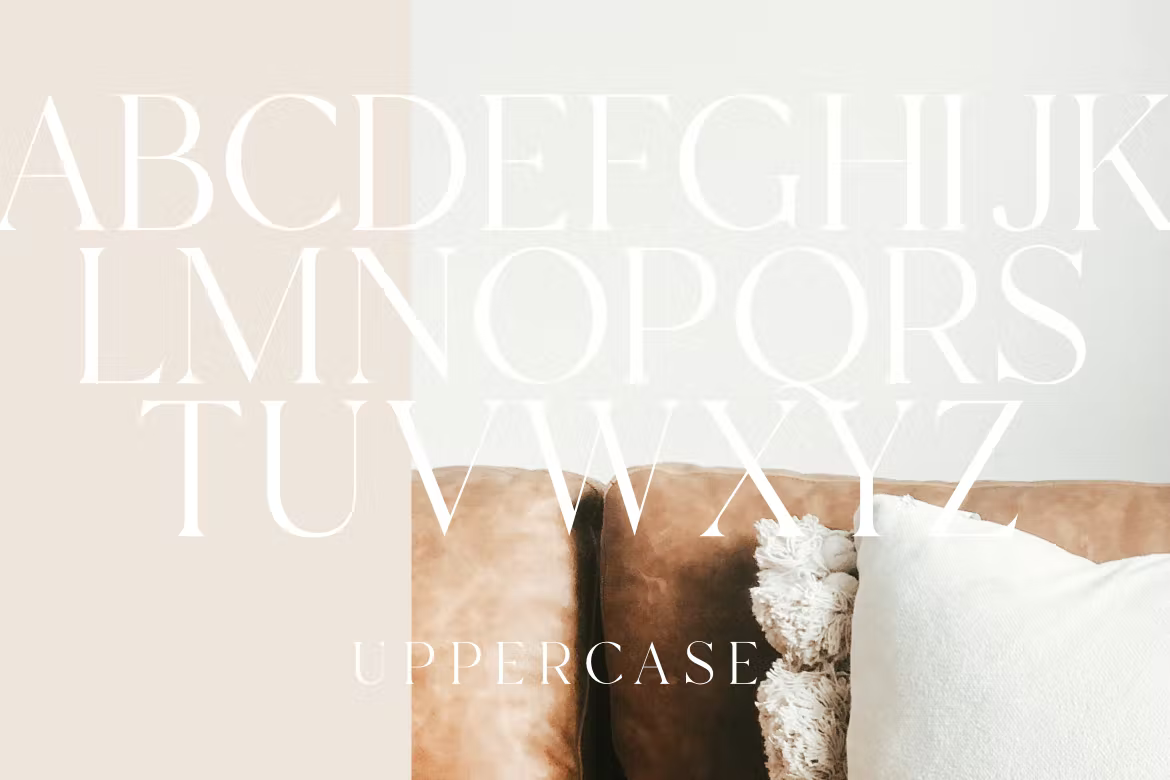
Branch Font
Description de Branch Font
Branch Font Elegant Ligature Font par Sans and Sons présentant notre nouvelle ligature moderne « Branch » avec un style élégant, parfaite pour l’image de marque, les logos, les invitations, les titres de mât et plus encore.